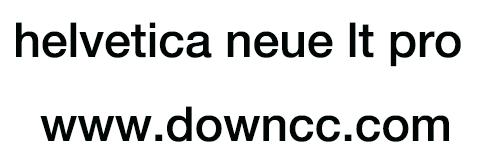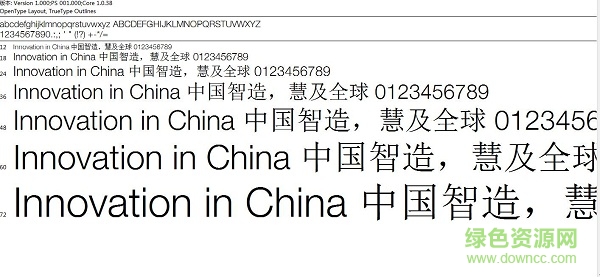
helvetica neue lt pro字體包收錄了helveticaneueltpro lt字體、helveticaneueltpro bd字體、helveticaneueltpro roman字體等七款無襯線字體,顯示效果良好,歡迎大家在本站免費下載!
中性也是一把雙刃劍,冷靜,客觀的同時,也抹殺情感和活力,忽略了形式可能為讀者帶來的情感體驗。